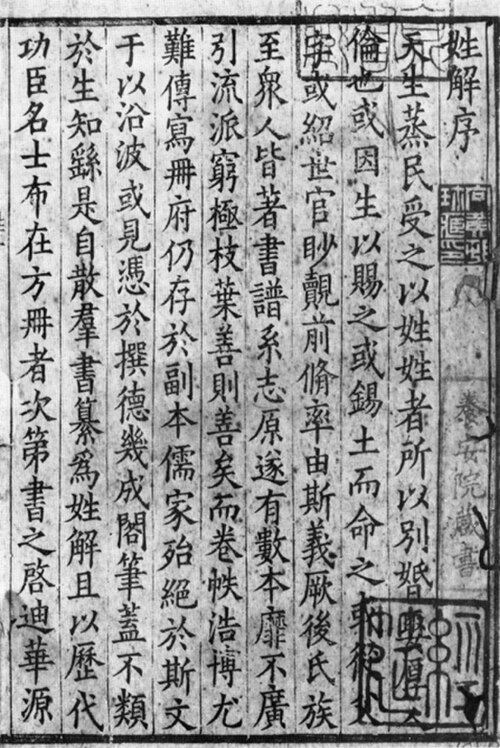
| 明朝体 | |||||||||||||||||||
| 中国語名 | |||||||||||||||||||
| 繁体字中国語 | 明體 | ||||||||||||||||||
| 中国語(簡体字) | 明体 | ||||||||||||||||||
| 文字通りの意味 | 明朝体 | ||||||||||||||||||
| 歌 | |||||||||||||||||||
| 繁体字中国語 | 宋體 | ||||||||||||||||||
| 中国語(簡体字) | 宋体 | ||||||||||||||||||
| 文字通りの意味 | 歌の書体 | ||||||||||||||||||
| 韓国名 | |||||||||||||||||||
| ハングル | モージョウ | ||||||||||||||||||
| 漢字 | 明朝体 | ||||||||||||||||||
| 日本語名 | |||||||||||||||||||
| 漢字 | 明朝体 | ||||||||||||||||||
| 仮名 | みんちょうたい | ||||||||||||||||||
明朝体または宋体は、中国語、日本語、韓国語で使用される漢字を表示するために使用される書体のカテゴリです。現在、中国語と日本語の印刷では最も一般的な書体です。日本語と韓国語のテキストでは、それぞれ明朝体と明朝体と呼ばれます。
名前
宋(またはSung)と明という名前は、独特の楷書体が開発された宋王朝と、そのスタイルが明書体スタイルに発展した明王朝に対応しています。 [1]中国本土では、最も一般的な名前はSongです( Microsoft Windowsで中国本土標準化された明書体はSimSunと呼ばれています)。香港、台湾、日本、韓国では、Mingが普及しています。香港と台湾では、「宋体」書体が伝統的に使用されてきましたが、「明體」書体はデスクトップパブリッシングの出現以来人気を博しています( Microsoft Windowsで繁体字標準化された明書体はMingLiUと呼ばれています)。一部のフォントファウンドリー[2]は、「正体国字」などの 標準に準拠したこのスタイルの書体を指すために「宋」を使用し、「康熙字典」にある形式に似た書体を指すために「明」を使用しています。
特徴
明朝体の特徴は次のとおりです。
- 楷書体の基本構造
- 太い縦線と細い横線が対照的
- 日本語では「鱗」と呼ばれる水平線の端にある三角形は、セリフに相当します。これは、筆を止める(dùnton)ことによって生じるわずかな点の印刷版です。この「休止技法」は、楷書体の特徴である、筆の始めや終わりを強調するために使用されます。
- 全体的な幾何学的規則性
可変の線の太さと、セリフに似た行末の特徴的な装飾を備えたこの書体は、西洋のサンセリフに相当する東アジアのゴシック書体とは対照的に、西洋のセリフ書体に匹敵します。
バリエーション
同じ漢字でも書き方が異なる場合が多く、これらをまとめて異体字と呼びます。違いの一部は文字の簡略化によるものですが、その他は単に筆画のスタイルなど正書法上の違いです。明代の古い書体で使用されている筆画のスタイルは、康熙字典で使用されているスタイルに由来しています。[要出典]
中国本土では、現代の標準化された文字形式は、現代中国語常用文字リストに指定されています。リスト内の一部の文字は、単に簡体字であるという理由で康熙文字と異なりますが、他の文字は異なる異体字または綴り法を使用しているために異なります。
台湾では、国字標準が現代の標準化された形式を規定している。中国本土の標準とは異なり、台湾の標準は主に既存の文字形式を使用しているが、楷書体を参考にし、楷書体に基づいて明代の書体を広範囲に改革しており、多くの人々から批判を集めていた。[3] [4]
戦後の日本の漢字改革後、康熙字体の大半は旧字体と呼ばれ、改革された字体は新字体と呼ばれたため、新しい辞書では両方の字体を組み込むか、康熙字体を省略するようになった。韓国では、ほとんどの書体は康熙字体を使用している。
多くの漢字の印刷形式と筆記形式の間には違いがあります。これは銅版印刷とほとんどの人の手書き文字の間に違いがあるのと同じです。これらの違いの一部は永続的でスタイルに特有ですが、その他の違いは個々の書体の違いほど重要ではない場合があります。これらの違いは通常、読みにくくなることはありません。
歴史
中国
唐代の印刷産業は宋代に頂点に達し[1]、その時代には3つの主要な生産分野がありました。
- 浙江省では欧陽詹の楷書を模倣した出版物が出版された[1]
- 四川省では、顔真卿の楷書を模倣した出版物が出版された[1]
- 福建省では、出版物は劉公権の楷書を模倣した[1]
宋が金朝に中国北部の支配権を奪われると、その首都は臨安(現在の杭州)に移され、そこで印刷術、特に金朝に征服された場所に残された唐の文献の出版が復活した。臨安には多くの出版社が設立され、その中には陳起(中国語:陳起)が設立した陳宅書籍鋪(Chén zhái shūjí pù )も含まれていた。[1]そこからの出版物は、整然としたまっすぐなストロークを持つ独特の楷書体を使用していた。このスタイルの現代の書体は、模倣宋書体(簡体字:仿宋体、繁体字:仿宋體)に分類されている。明代には、臨安の出版物の再版でストロークがまっすぐになったことが、明のスタイルの基礎となったものへの移行の始まりとなった。[1]
Chén zhái shōjí pùの出版物のページ。
日本
明朝体(明朝、Ming Dynasty)は、日本の印刷物で最も一般的に使用されている書体です。教科書体や新聞体など、いくつかのバリエーションが使用されています。
日本の近代活版印刷術の創始者である本木昌造(または元木)は、1869年にアメリカ人のウィリアム・ギャンブルから電解方式の活字製造法を学び、中国で普及していた活字を手本にしました。その後、本木はギャンブルによる中国聖書の文字頻度研究に基づいて、日本語の文字を追加した完全な活字セットを作成しました。日本語のテキストでは、中国語とラテン文字に加えて、ひらがなとカタカナの音節文字が使用されています。
韓国
韓国語では、最近まで日本語の用語の影響を受けて、ハングルのアルファベットの類似の書体は、明朝(同じ漢字「明朝」の韓国語読み)と呼ばれていました。1993年に文化省が後援したタイポグラフィ用語の標準化により、明朝は「基礎」または「地」(「図」の反対)を意味する韓国語の「バタン」(「바탕」)に置き換えられ、これが書体の現在の用語となっています。
コンピュータにおける明朝体
技術的には、明朝体で印刷できるのは中国語の文字だけです。ただし、ほとんどの現代の書体 (つまり、デジタル書体) には、一致するスタイルで仮名文字も含まれていることが多く、通常は筆で手書きしたような正確なスタイルです。現代の明朝体には、ラテン文字、文字のような記号、数字のローマ字文字も組み込まれています。西洋のセリフ書体に相当する現代の役割では、仮名文字とラテン文字の両方が、通常、完全な書体の一部となっています。
明朝体は中国、日本、韓国の政府によって公式に使用されています。